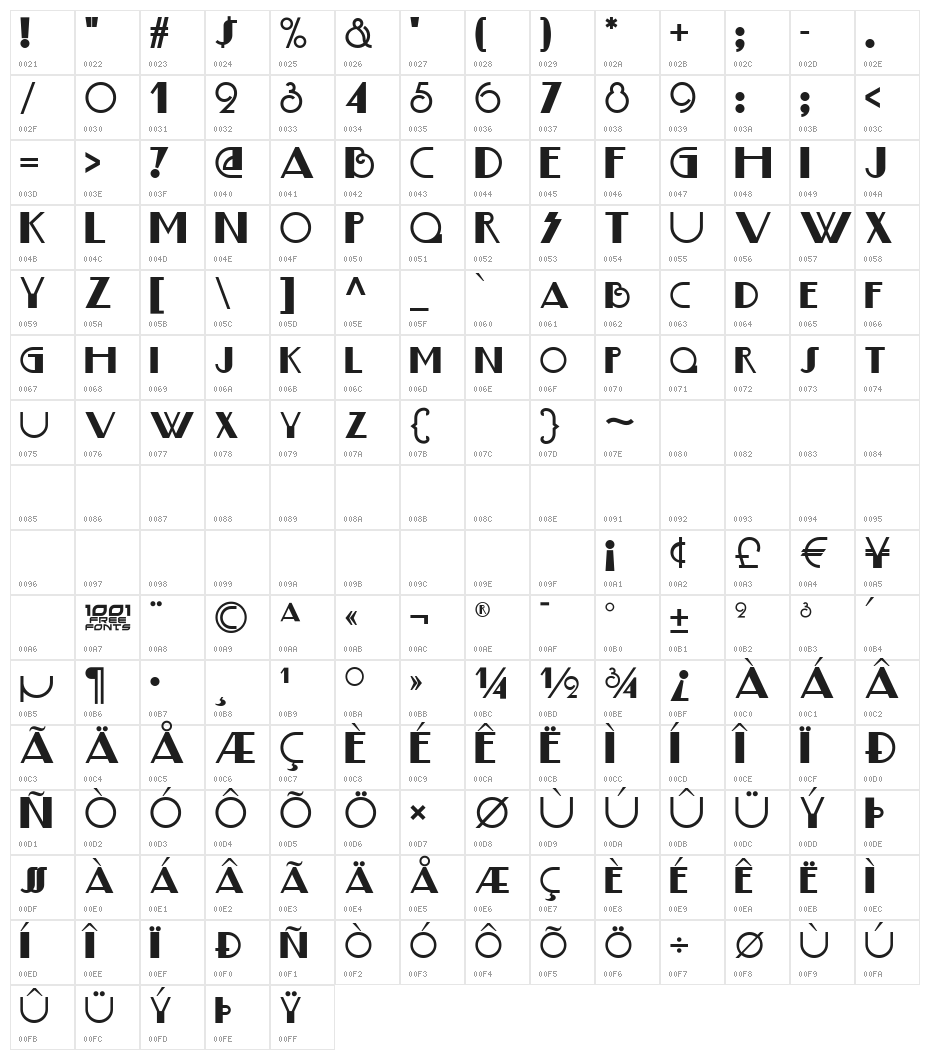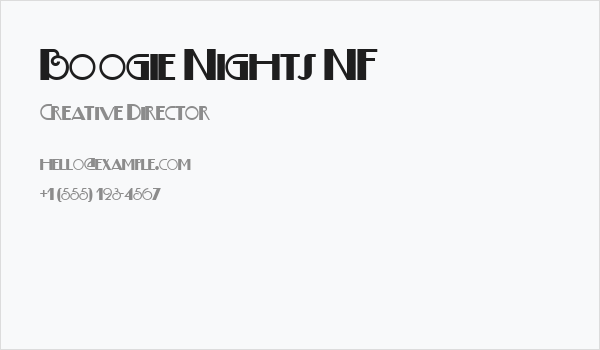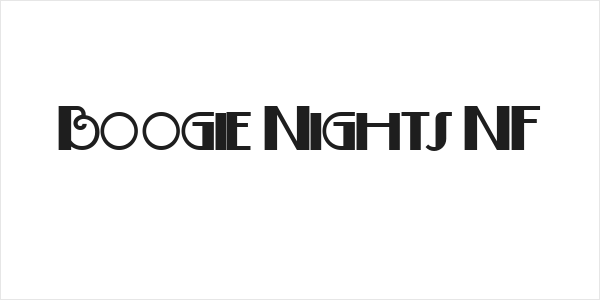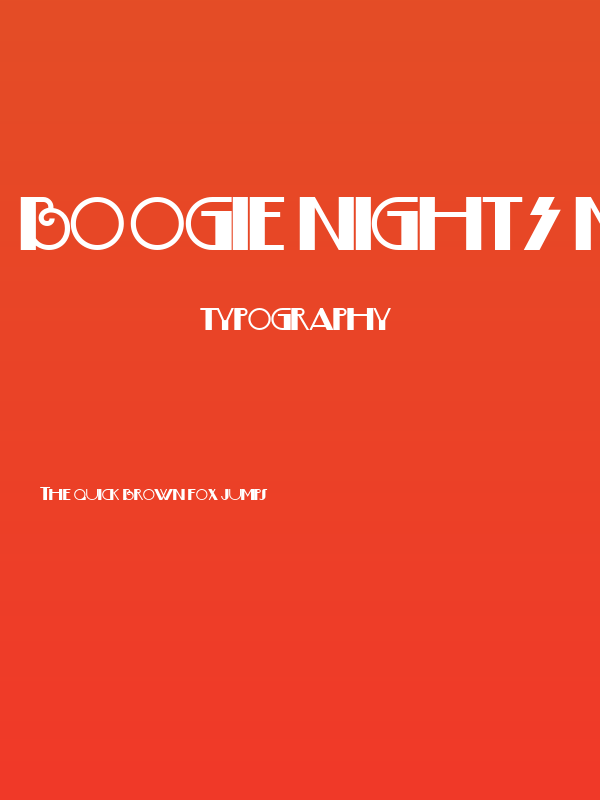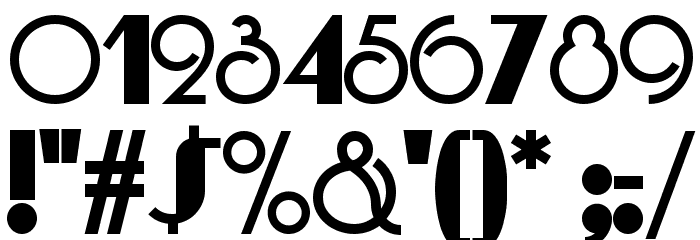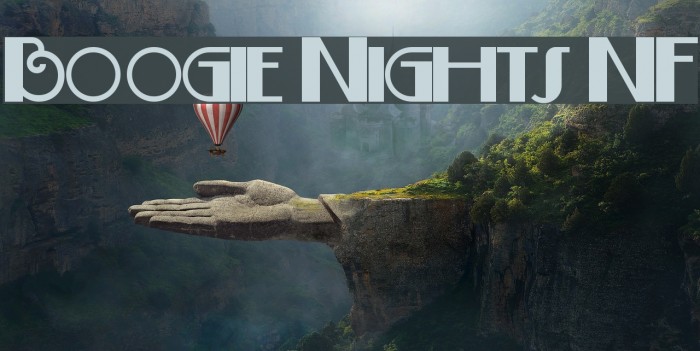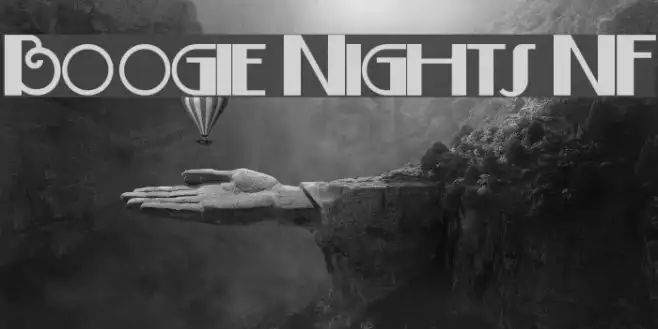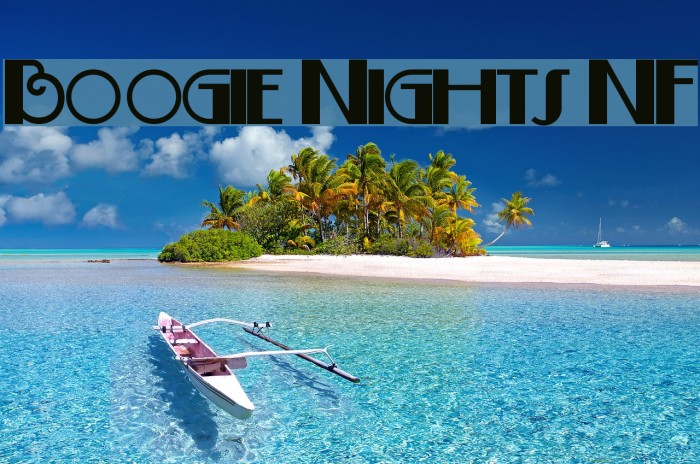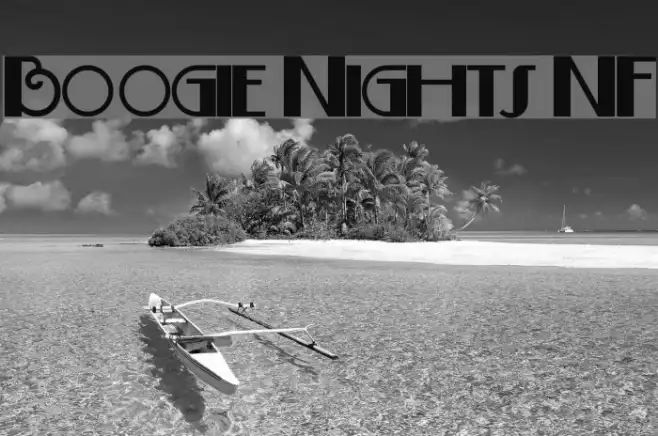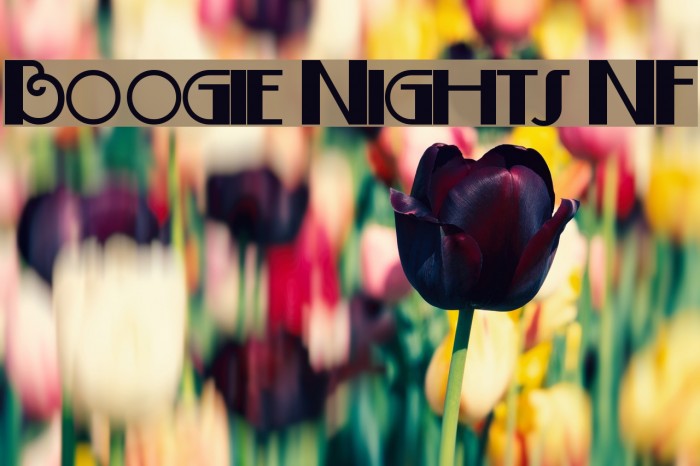
Boogie Nights NF Font
| Gesamtstil | Vintage |
| Vorgeschlagene Projekte | Ideal for retro-themed posters, music album covers, event flyers, and branding that seeks a vintage or playful touch. |